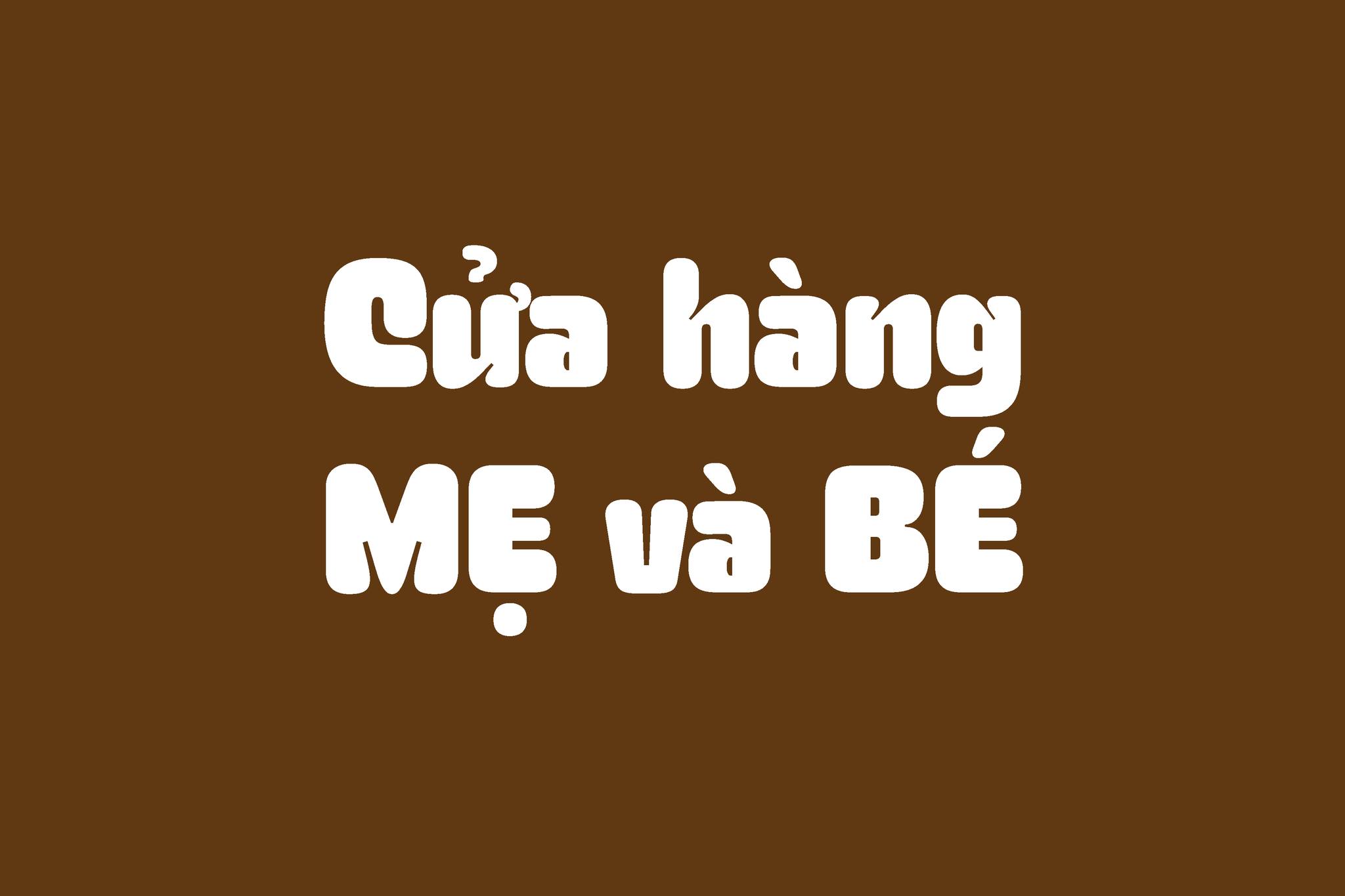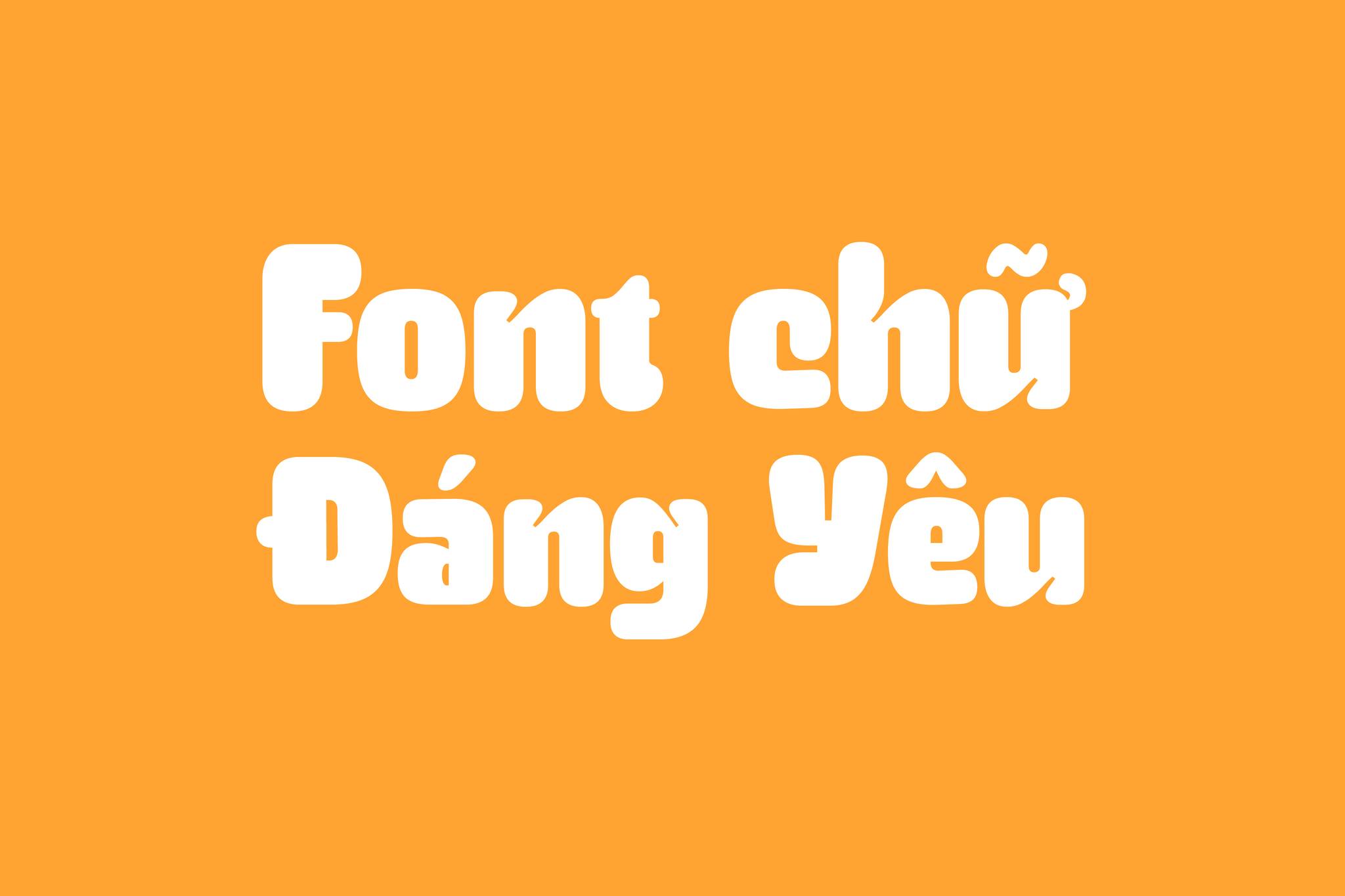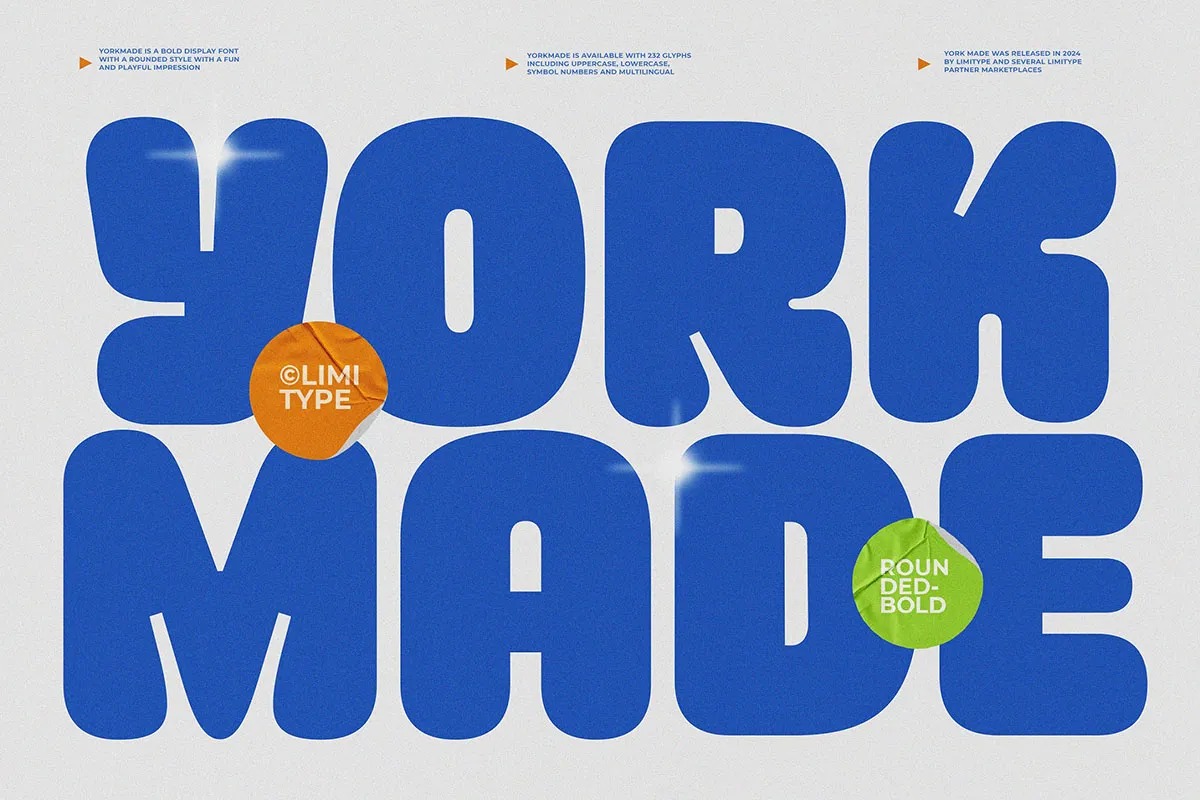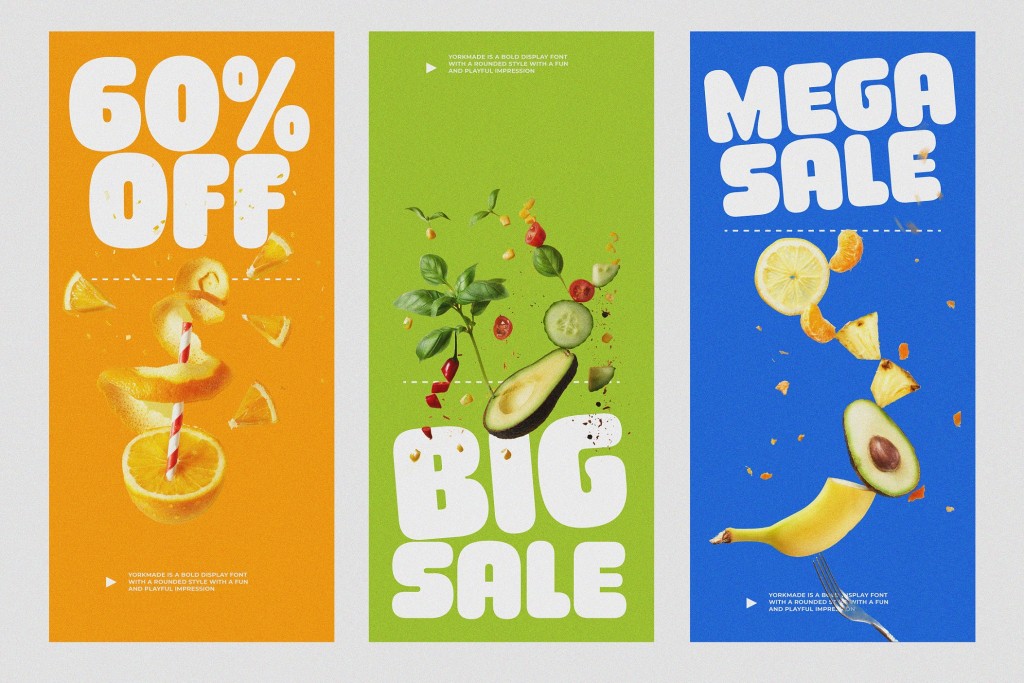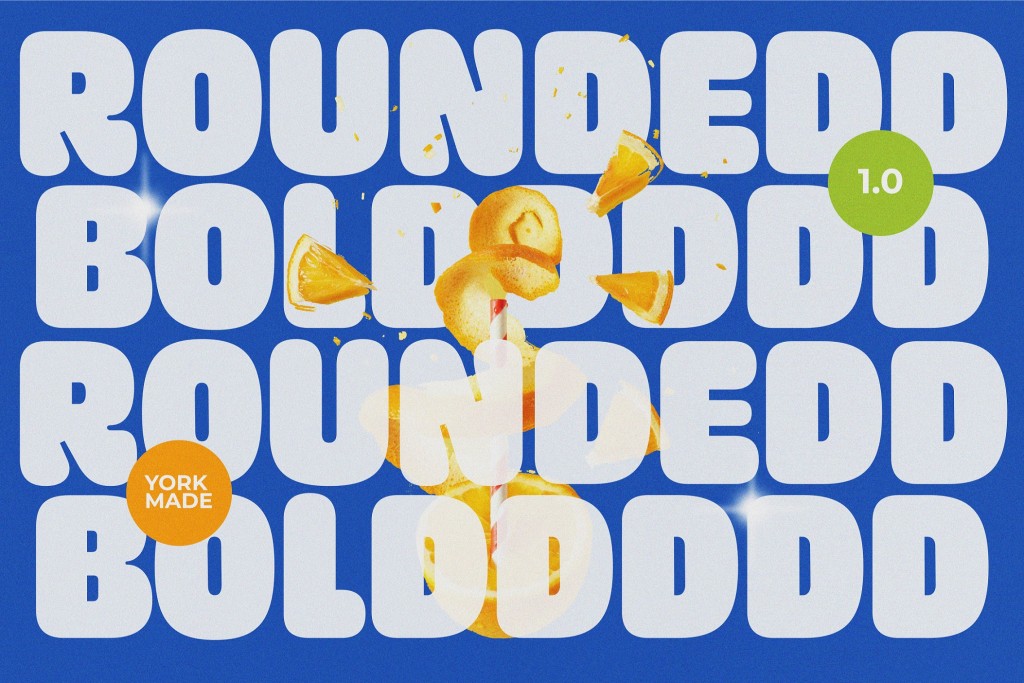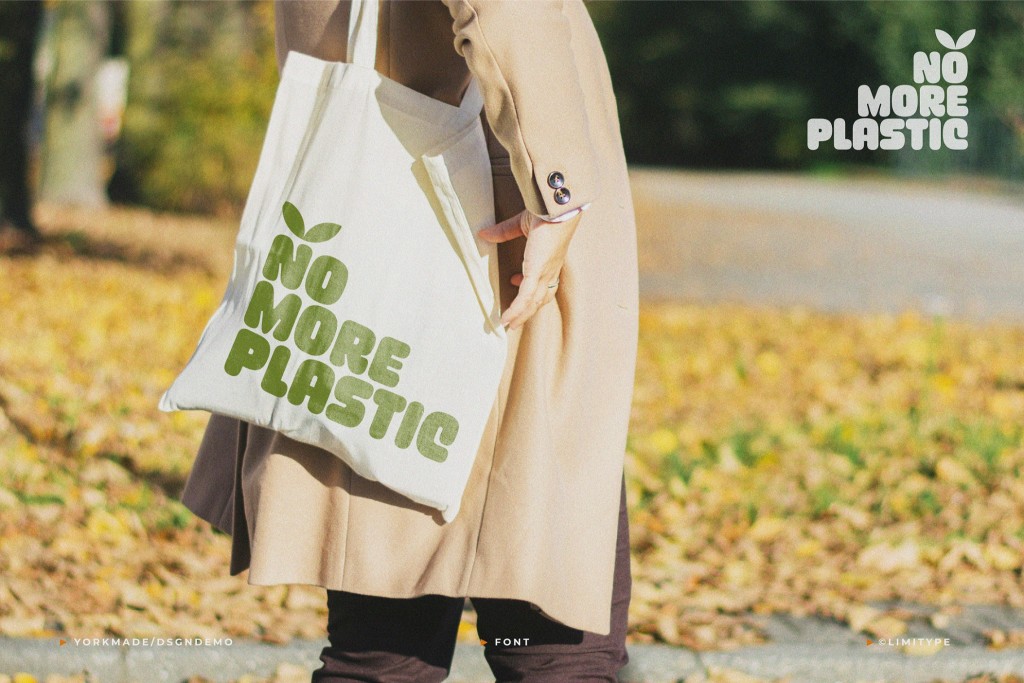
Font chữ Yorkmade Việt hóa – Nét chữ bo tròn vui nhộn cho thiết kế hiện đại
TH Yorkmade là một font chữ bo tròn (rounded display font) được thiết kế bởi Muhammad Muammar và phát hành bởi Limitype Studio. Phiên bản Yorkmade Việt hóa đã được tinh chỉnh kỹ lưỡng để hỗ trợ đầy đủ tiếng Việt, bao gồm toàn bộ dấu thanh và ký tự đặc trưng – mang lại trải nghiệm thiết kế mượt mà, đồng nhất và không lỗi font.
Điểm đặc trưng nổi bật của Yorkmade nằm ở đường nét dày dặn, bo tròn và gọn gàng, gợi cảm giác vui tươi, thân thiện và có phần hiện đại. Các chi tiết inktrap nhỏ giúp font có chiều sâu và dễ nhận diện hơn trong các thiết kế mang tính thương hiệu hoặc trẻ trung.
Font phù hợp để sử dụng trong nhiều loại hình thiết kế, từ bao bì sản phẩm, tiêu đề poster, logo sáng tạo cho đến các ấn phẩm hướng tới đối tượng thiếu nhi. Với phiên bản Việt hóa, Yorkmade có thể dễ dàng tích hợp vào thiết kế web, đồ họa in ấn và các dự án sáng tạo yêu cầu hỗ trợ tiếng Việt trọn vẹn.
Nếu bạn đang tìm kiếm một font chữ bo tròn, hiện đại và mang tinh thần tích cực cho dự án của mình, Yorkmade Việt hóa là lựa chọn đáng cân nhắc. Không chỉ đẹp về hình thức, bộ font này còn cho thấy sự đầu tư chỉn chu trong việc Việt hóa – đáp ứng đầy đủ tiêu chí về trải nghiệm người dùng và hỗ trợ ngôn ngữ.